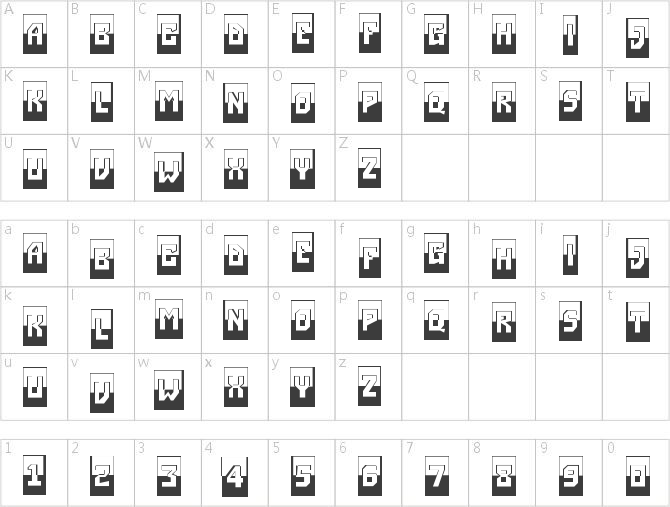
a_simplercmbw bold
a_simplercmbw bold介紹
a_simplercmbw bold字體字庫是一款讓人賞心悅目、百看不厭的英文字體,適合各類廣告和產品包裝設計應用,字體大小0.05MB,格式為ttf字體,上傳用戶是373790005,作者/版權方為未知
a_simplercmbw bold效果圖